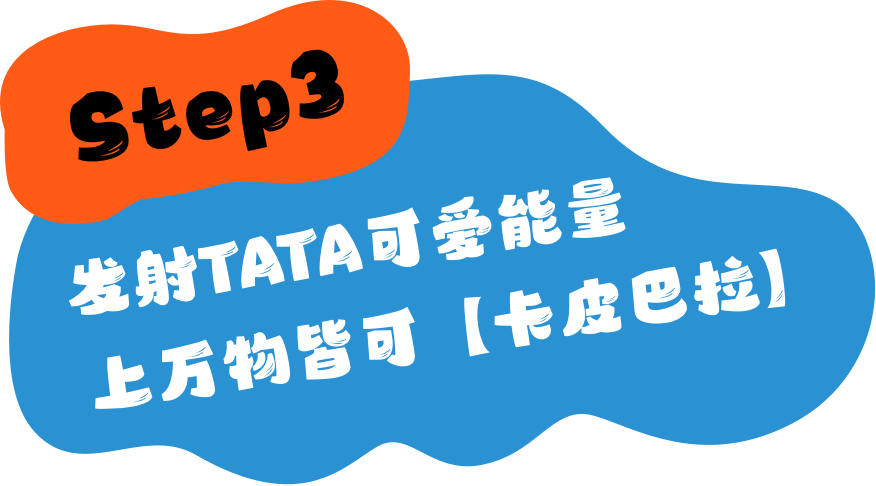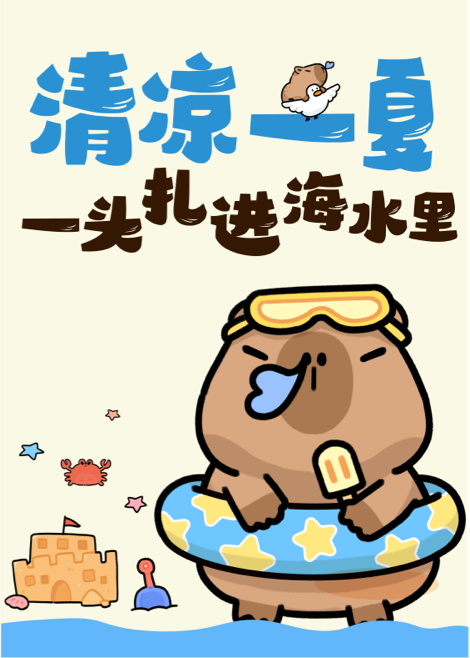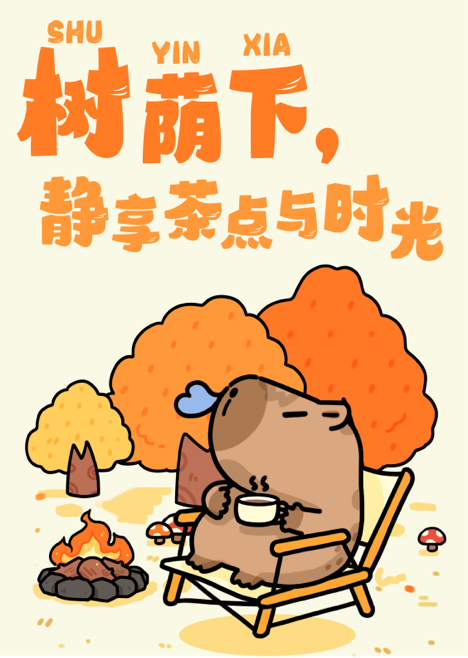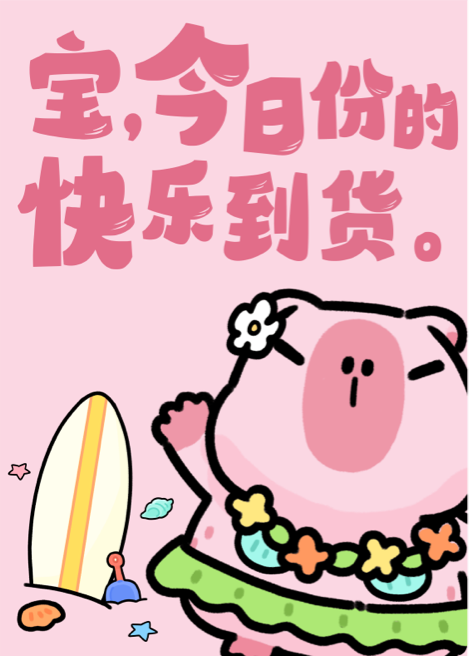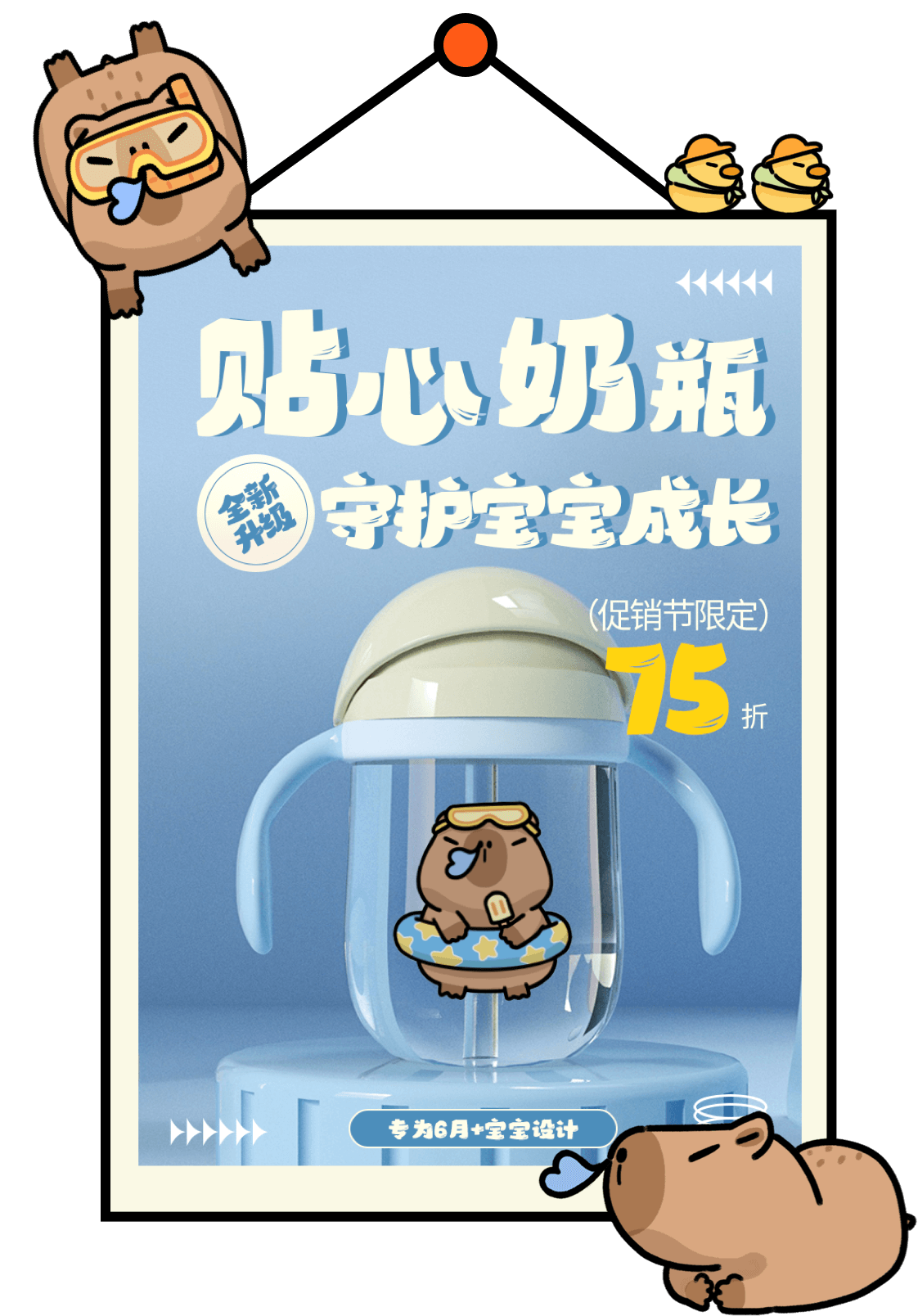
TATA是一只来自巴拿马的母水豚,今年5岁了。一直生活在三里屯的TAKARA萌宠乐园。在日常遛弯时被街拍,视频浏览量爆火,再加上刚好有一首洗脑神曲《卡皮巴拉》洗脑,使得全网迎来“水豚热”。
字魂创意字库与TATA家族进行跨界合作,开发了这一款颇有【卡皮巴拉】独特灵魂的萌趣字体,并在字魂创意字库官网上线。
字魂卡皮巴拉体从水豚的神态中提取灵感,字形宽扁憨粗,采用圆润、稚拙的笔触,复刻TATA给人的可爱联想。字体笔画上,设计了微翘和高光的细节,增添了活泼和生动之感。
字魂卡皮巴拉体稚气可爱,亲切萌趣,十分具有视觉感染力,在儿童、母婴、萌宠、餐饮等商业领域能得到广泛的应用。不论是产品包装、品牌宣传或是周边设计,这款字体都带来丰富的排版装饰效果。